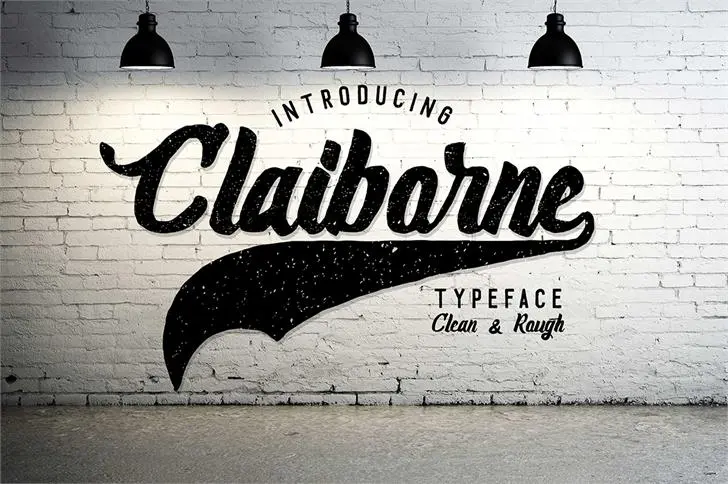
Claiborne Typeface – Download Grátis
Bem-vindo ao mundo deliciosamente detalhado dos scripts com a fonte Claiborne Typeface! Criada por madeDeduk, essa fonte Script se destaca entre as demais por sua naturalidade e elegância, proporcionando um gráfico fluido que transmite confiança e sofisticação em qualquer projeto. O nome Claiborne refere-se a uma cidade famosa por suas belas paisagens, o que não poderia ser mais adequado para essa fonte tão bonita. A madeDeduk oferece esta fonte em versão de doação, então se você deseja explorar sua totalidade e toda a sua capacidade incrível, basta clicar no link abaixo. Junte-se à nós neste mundo de letras belas e únicos!